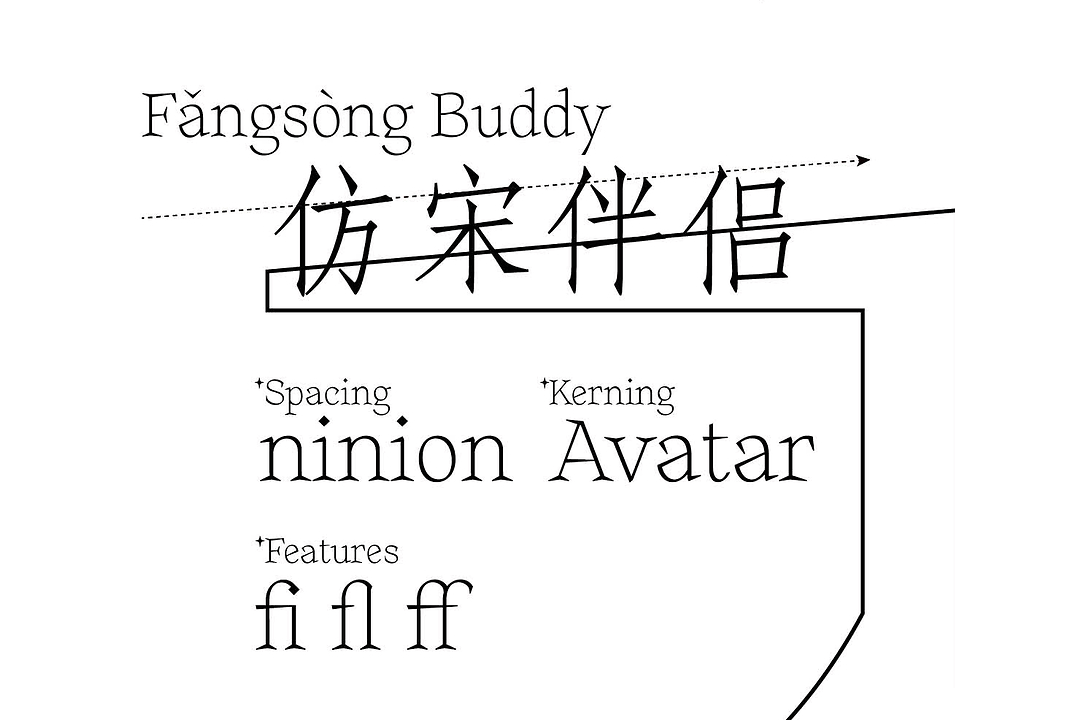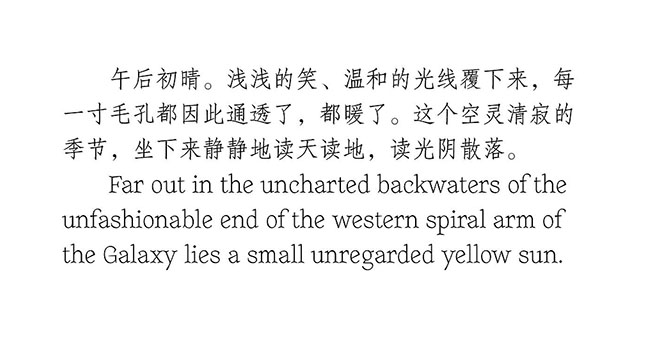
仿宋伴侣(FangsongBuddy)是由站酷设计师figovision(UID:1042506)创作的一款免费可商用英文字体。该字体通过系统性调整中西文字形的视觉特征,实现了二者在混排时的气质融合,这在日常中西文混排时尤为重要。
1、字形结构硬朗、简洁,笔画粗细均匀,与仿宋硬朗的气质协调;
2、在西文横笔画中有意进行了左低右高的设计细节,引导视觉与仿宋的横笔画进行统一;
3、采用较为尖锐的衬线与仿宋的笔画(比如勾、点)进行风格统一;
4、字间距较为宽松,与现有仿宋字库宽松的字间距进行匹配,版面灰度均衡;
5、仿宋作为工程制图中常用的标注字体,其数字也经过精心设计,斜线0也是较为流行的表达方式;
6、补全汉语拼音韵母,满足常见的应用场景。
该字体特别适用于需要中西文混排的设计场景,通过视觉校准实现无缝衔接的排版效果。